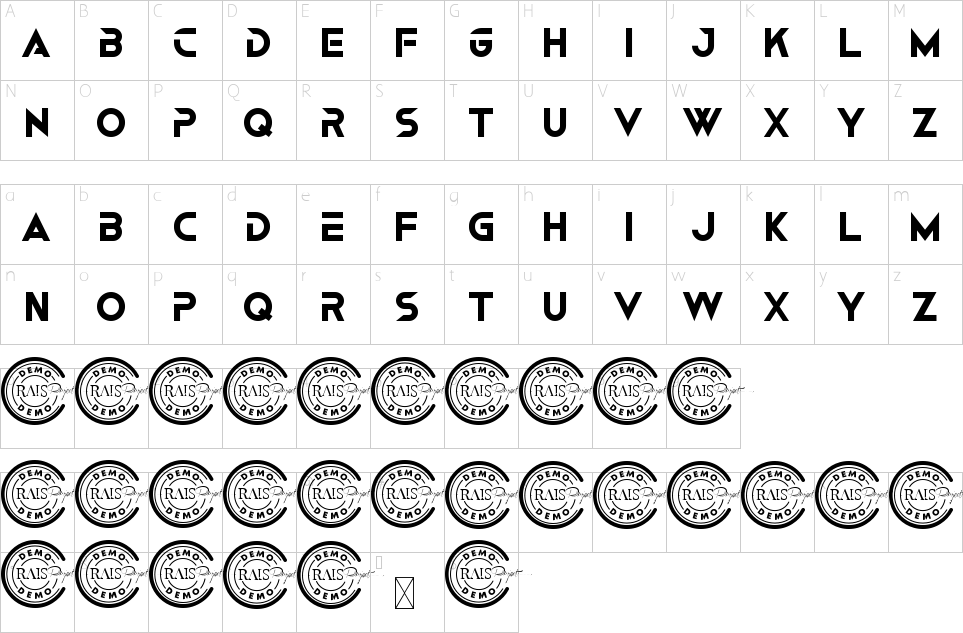
A Font Dragraces é uma opção atraente para designers que buscam incorporar elementos dinâmicos e modernos em seus projetos digitais. Desenvolvida pela equipe da raisproject, ela se destaca por sua capacidade de criar efeitos visuais interessantes, especialmente na criação de elementos gráficos e icones. Este é um font gratuito disponível tanto para Windows quanto para Mac, oferecendo uma variedade de opções para aqueles que desejam incorporar detalhes atraentes sem custos adicionais. Com sua simplicidade e flexibilidade, Dragraces torna-se uma escolha ideal para designers gráficos buscando personalizar seu layout com rapidez. A font é projetada para complementar um amplo range de estilos e formatos, desde o moderno até os mais tradicionais, garantindo que a sua marca seja sempre reconhecível e única. Com menos de cinco mil downloads no total, Dragraces é uma opção relativamente nova mas já conquistou espaço entre designers atentos à criatividade na web e nas mídias digitais.